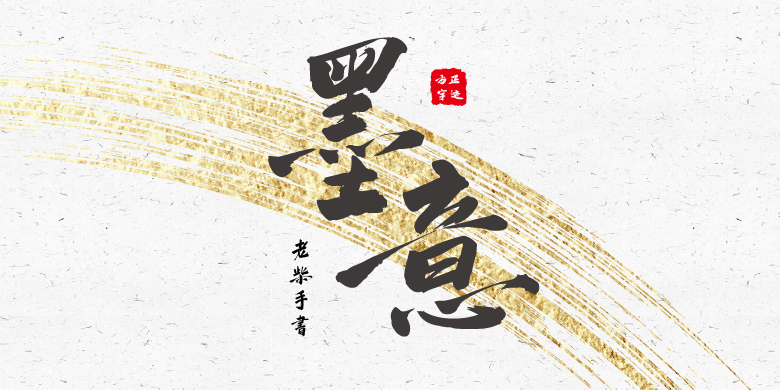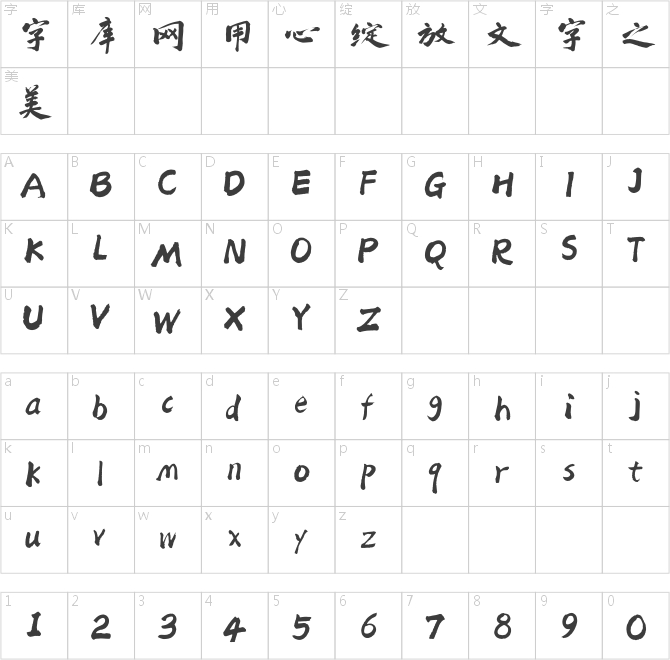
方正字跡-老柴手書 詳情頁
字體名稱: 方正字跡-老柴
方正字跡-老柴手書
方正字跡-老柴手書是一款傳統(tǒng)書法與現(xiàn)代設(shè)計(jì)相結(jié)合的創(chuàng)意書法字體,字體蒼勁有力,豪放大氣,適合海報(bào)等大標(biāo)題廣告宣傳領(lǐng)域。作者柴海軍,小米公司設(shè)計(jì)師、小米書法協(xié)會(huì)會(huì)長。